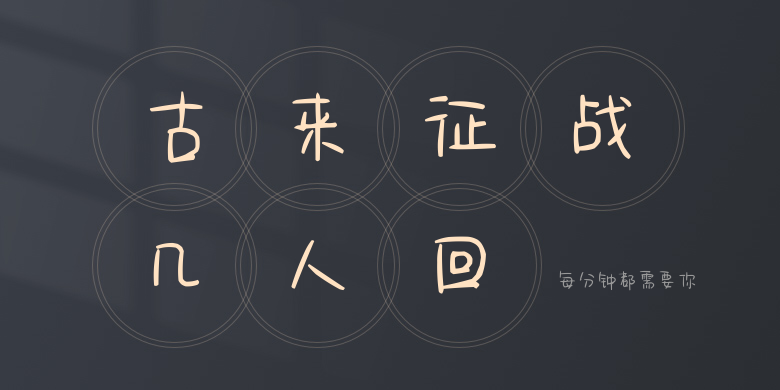
每分钟都需要你
每分钟都需要你,这款字体结构工整、笔画清晰,兼顾美观与易读性,适用于标题、正文、海报、包装、LOGO 等多种场景。字形优雅稳定,风格百搭耐看,适配日常排版与创意设计,让文字呈现更舒适、更具质感。每分钟都需要你一笔一画,皆是细节,以均衡的比例、流畅的线条打造舒适视觉体验,字形端正大气,风格简约现代。无论是商业设计、品牌宣传还是日常排版,都能轻松驾驭,让文字更有格调与力量。每分钟都需要你字体下载。